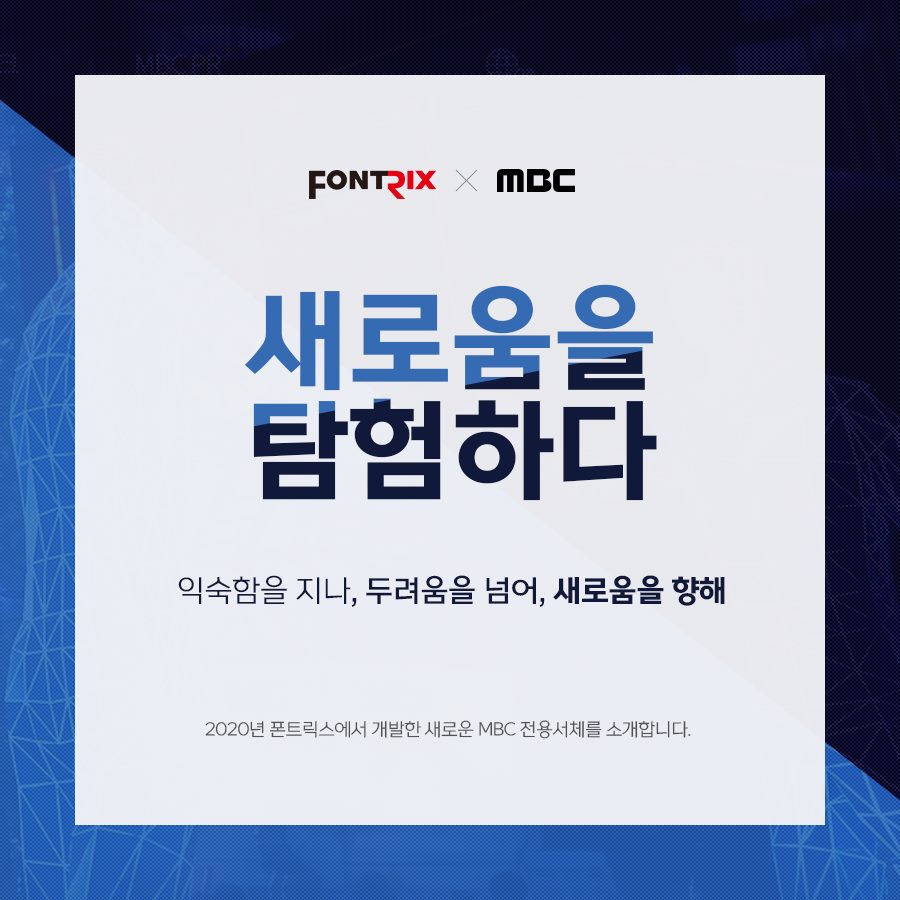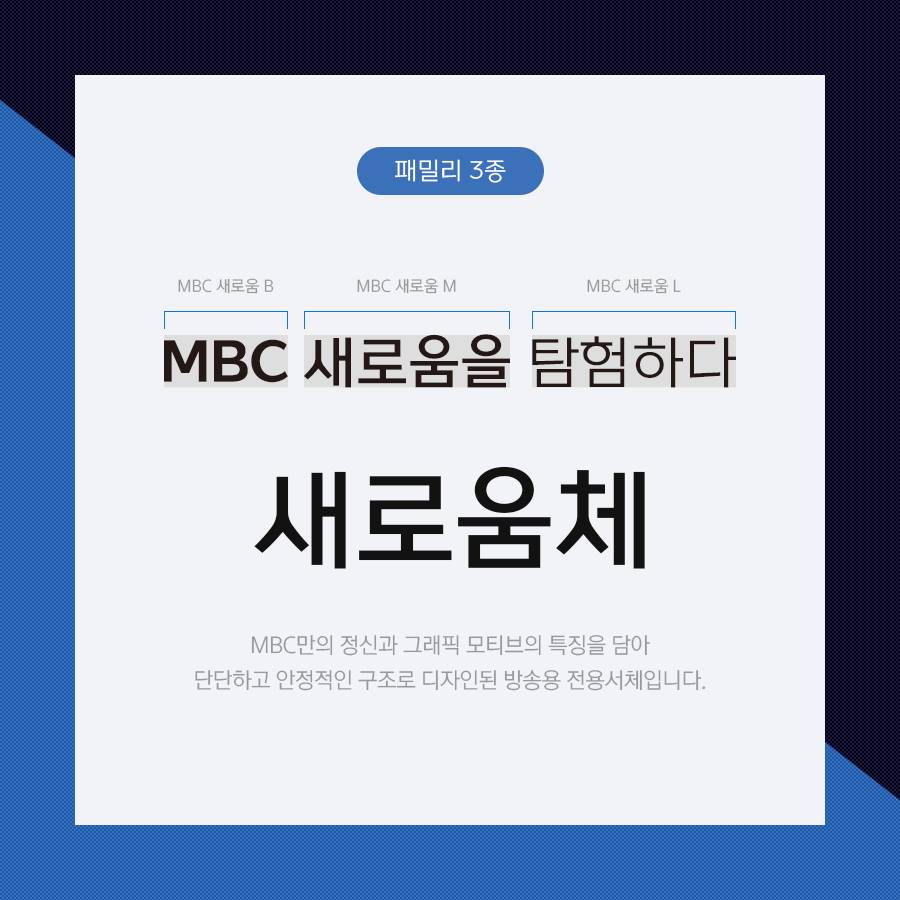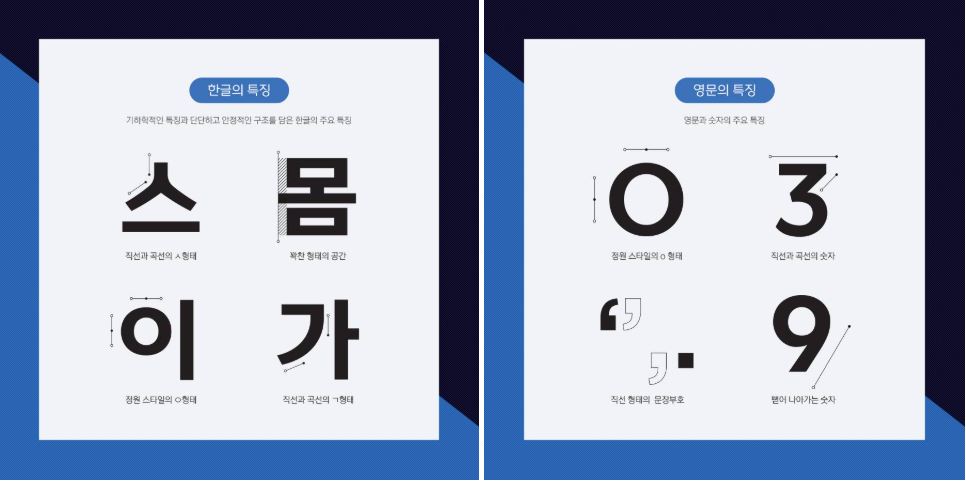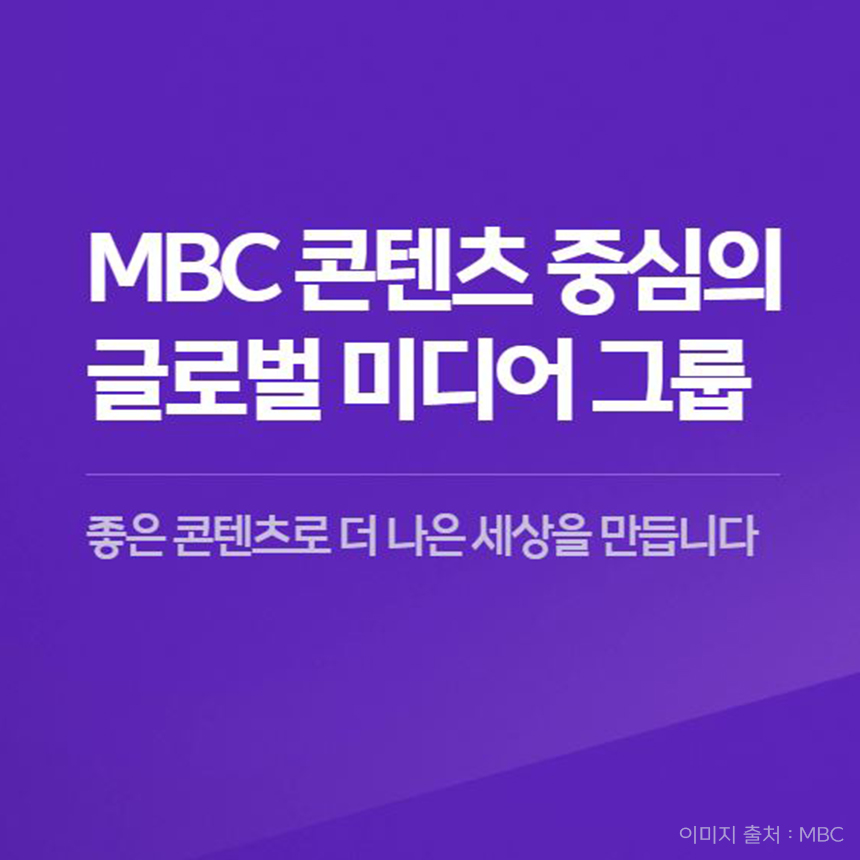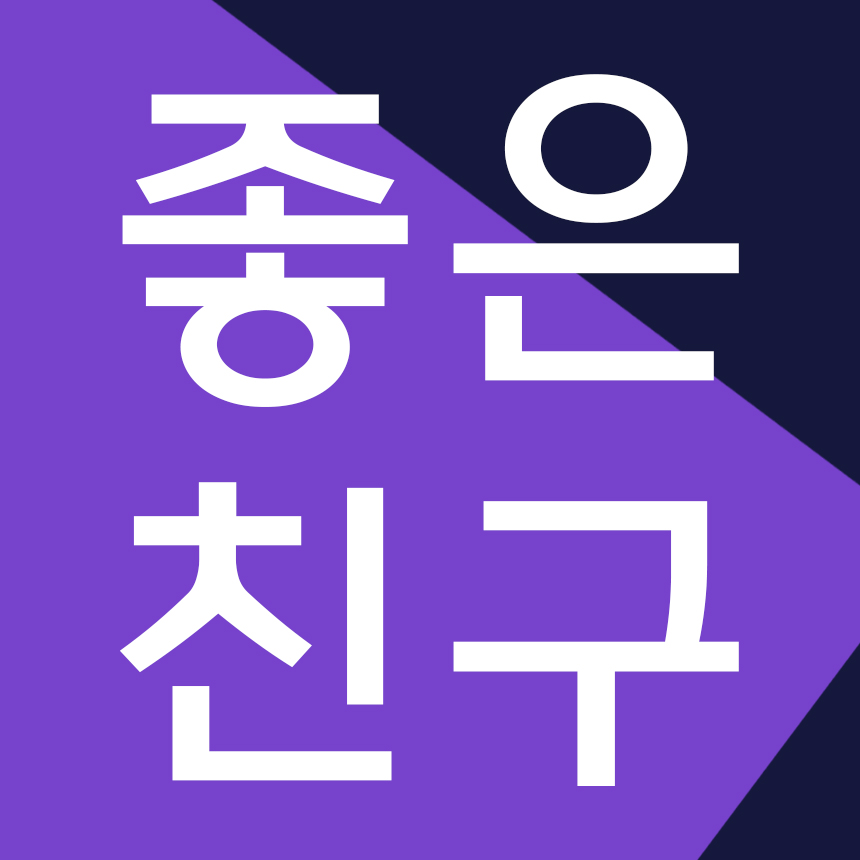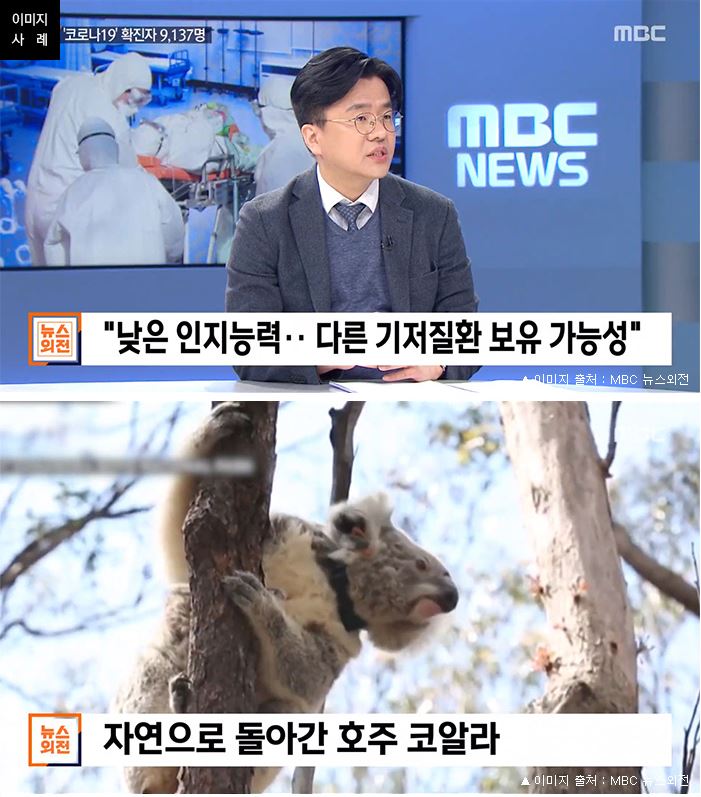
안녕하세요. 오늘은 대한민국 대표 지상파 방송사 중 하나인 MBC의 전용서체로 제작한 「새로움체」를 소개해드릴까 합니다! 먼저 이 전용서체를 개발하고 디자인해 주신 박용락 디자이너님의 이야기를 들어볼게요.
MBC 새로움체는 어떻게 제작하게 되었나요?
원래는 MBC 그래픽팀 디자인용으로 제작하였는데 사내 반응이 좋아서 뉴스 자막에도 사용하게 되었습니다. 전용서체를 제작하면서 많은 클라이언트를 만나왔습니다. 모든 일이 그러하듯이 사람이 하는 일이기 때문에 누가 담당하느냐에 따라 일이 순조로울 때도 있고 굉장히 힘들 때도 있고, 회사의 보고체계나 담당자 권한의 정도에 따라 달라질 수도 있습니다. MBC의 경우는 디자인 팀장님께서 워낙 나이스~하게 진행해주셔서 아주 매끄럽게 잘 마무리되었습니다. 물론 믿고 맡겨주신 만큼 보답하기 위해 좀 더 신경 쓴 것도 사실입니다.
MBC 새로움체, 어떤 매력이 있나요?
MBC 전용서체는 정원의 지오메트릭한 요소와 획의 직선적인 요소를 더해 자칫 너무 귀여워지고 여성스러워질 수 있는 서체를 힘 있고 산뜻한 느낌이 날 수 있도록 디자인하였습니다. 그래서 귀여운 면과 또렷하고 힘 있는 이중성이 있는 서체라고 말씀드릴 수 있습니다. 사람도 폰트도 너무 예측 가능하면 매력이 없듯이 폰트에도 이렇게 이중성을 부여하면 새로운 아이덴티티도 도출되고 자주 봐도 질리지 않는 매력 있는 폰트가 됩니다.
제작 과정에서 중요하게 생각한 부분은 무엇인가요?
음식에 비유하자면 음식도 너무 자극적이면 금방 질릴 수 있습니다. 미묘하고 디테일한 맛을 컨트롤했을 때 깊은 맛을 느낄 수 있습니다. 폰트도 기본에 충실하면서 디테일이 있는 변화를 주면 자극적인 요소를 주지 않더라도 위에서 말한 새로운 맛이 있고 오래 먹어도 질리지 않는 폰트가 되겠지요. 처음 나왔을 때 잠깐 빛났다가 사라지는 폰트가 아닌 긴 생명력을 가진 폰트를 만들고자 하였습니다.
MBC 서체가 그렇게 되길 바라봅니다.
산뜻하고 더 새로워진, MBC 새로움체
'새로움체'는 MBC의 아이덴티티를 잘 보여줄 수 있도록 디자인했습니다. 뉴스뿐 아니라 교양, 예능 프로그램, 웹페이지 등 방송사의 여러 용도에 다양하게 쓰이도록 3가지 굵기로 활용도를 높였습니다.
자칫 너무 귀여워지거나 여성스러워질 수 있는 서체를 힘 있고 또렷한 느낌이 날 수 있도록 신경 쓴 디자인! 귀여우면서도 힘 있는, 이중성이 '새로움체'의 매력적인 요소가 되었습니다.
직선과 곡선을 잘 활용해 한글을 돋보이게 해주며, 꽉 찬 형태의 공간, 시원스레 뻗어나가는 선들이 신뢰감을 줍니다.
정확한 정보 전달이 중요한 뉴스에도 찰떡같이 어울리는 '새로움체'는 기본에 충실하면서 디테일한 변화로 신선한 느낌을 줍니다. 독창성과 가독성 모두 놓치지 않은 전용서체입니다.
이제 MBC에서 새로움체를 본다면 단번에 알아볼 수 있겠죠?